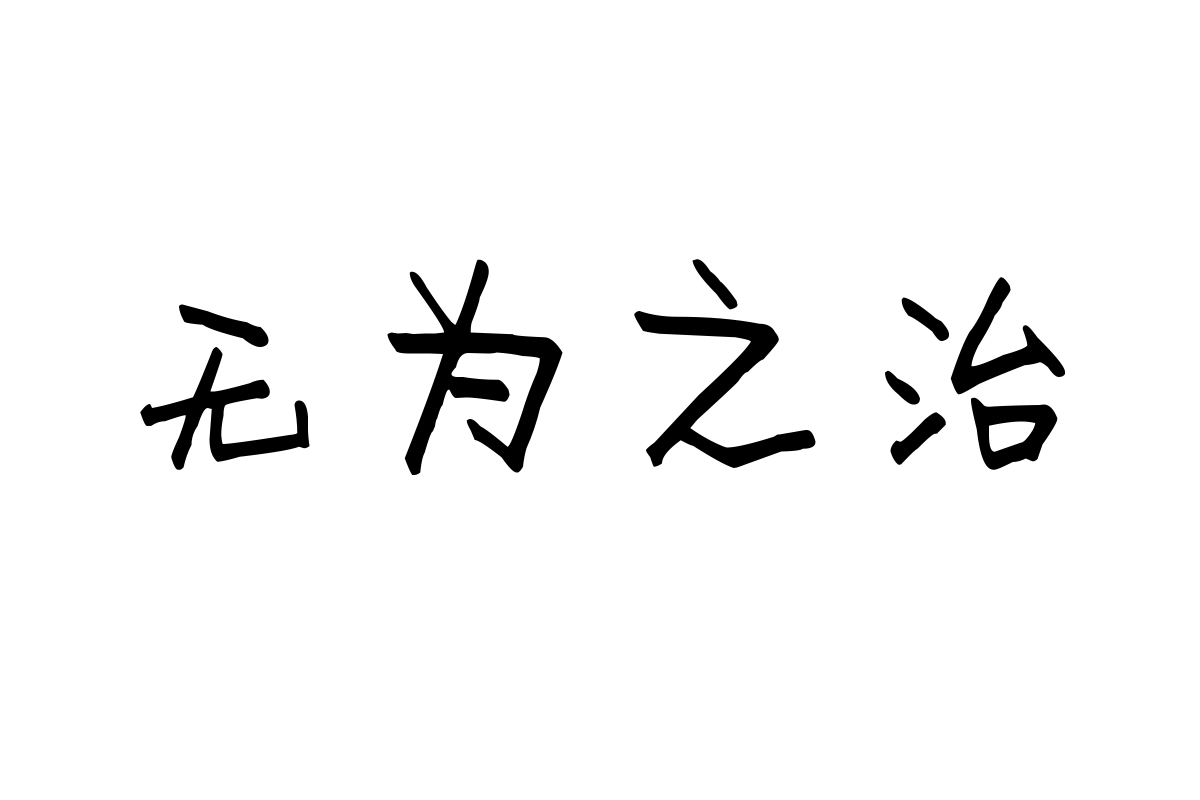
米开淘淘体字体是由设计师陈俊明设计的一款具有现代感和科技感的字体。它的特点是字形简洁,线条流畅,适合用于各种商业广告、品牌宣传等场合。
米开淘淘体字体的特点如下:
1. 字形简洁:每个字的笔画都经过精心设计,使得整个字体看起来简洁而有力。
2. 线条流畅:字体的笔画线条流畅自然,给人一种舒适的感觉。
3. 现代感:字体的设计充满了现代感,符合现代人的审美需求。
4. 科技感:字体的设计灵感来源于科技元素,使得整个字体充满了科技感。
5. 可读性强:字体的笔画粗细适中,既保证了阅读的舒适度,又保证了可读性。
总之,米开淘淘体字体是一款非常适合现代商业广告、品牌宣传等场合使用的字体。